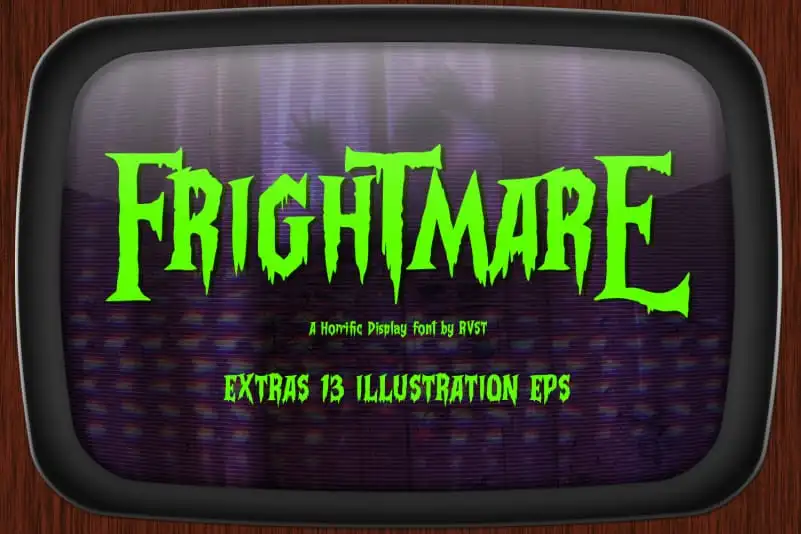
Frightmare – Display font – Fonte Grátis
Frightmare - Display font
Frightmare é uma fonte Display inspirada nas velhas grandes produções de horror que sempre fizeram parte do nosso imaginário cultural. Esta fonte leva você a essa era sombria e perturbadora dos anos 50 até hoje, onde o horror nos permeia de forma intensa. Frightmare tem sido projetado para ser acessível por meio da PUA Unicode, tornando o acesso a todas as alternativas caracteres muito mais fácil, especialmente útil para os designers que buscam expandir seu trabalho em profundidade. Com suas linhas escuras e tensas, Frightmare captura exatamente a atmosfera do terror. Através de seu design sóbrio e aparentemente frio, há um encanto sombrio oculto por trás de cada caractere, tornando-a uma escolha ideal para criar visuais que são tanto impactantes quanto intrigantes. Para os designers que buscam transmitir a essência do horror em suas criações digitais, Frightmare é uma fonte imperdível.